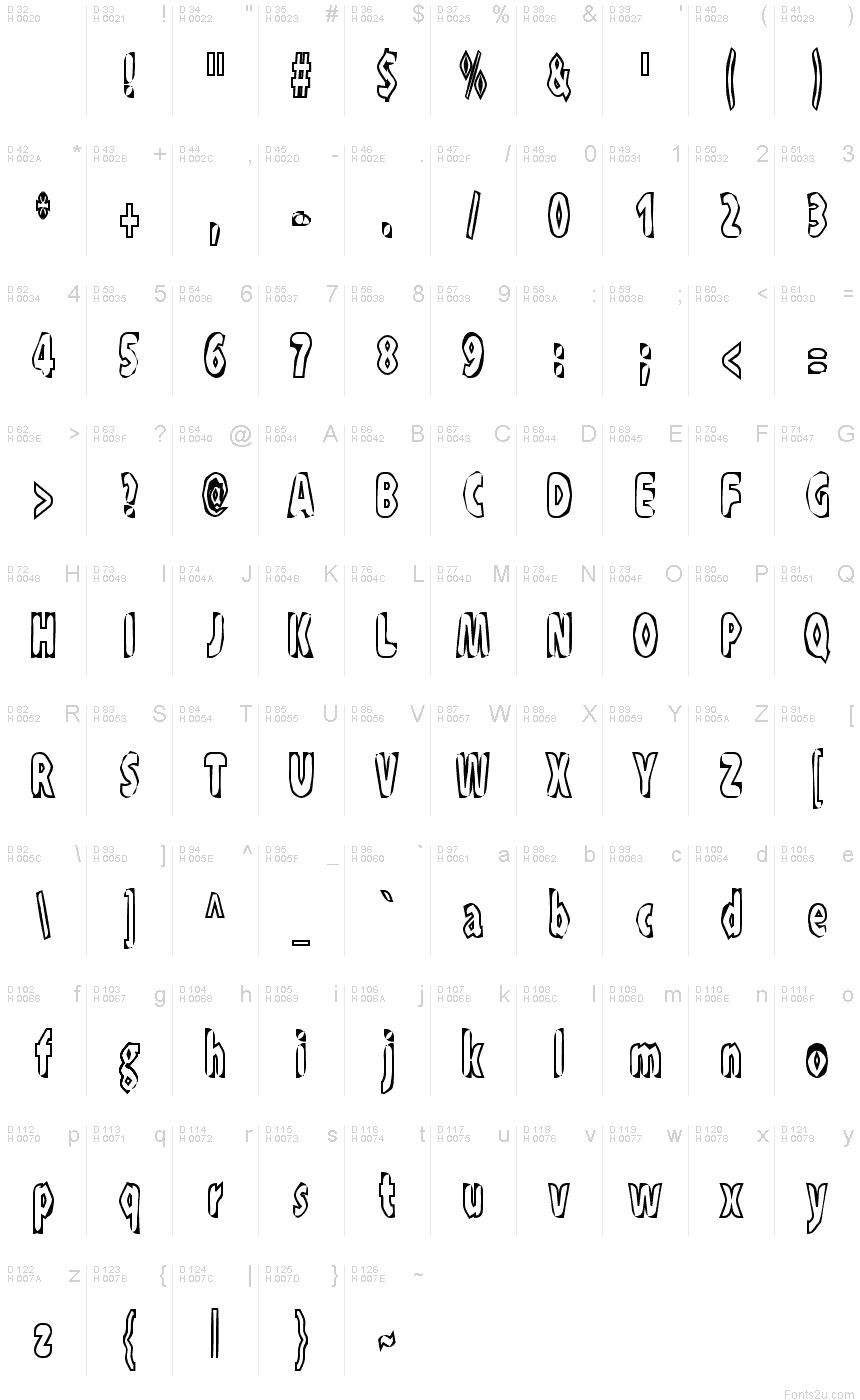
XRaytid od OMEGA Font Labs je bezplatný, deformovaný obrysový font s drsnou estetikou, která připomíná rentgenové snímky. Písmena kolísají mezi nabubřelými křivkami a staženými spoji, zatímco drsný dvojitý obrys dodává celému fontu elektrizující vzhled připomínající vystřihovánky, spíše než uhlazené komiksové tvary.
Hodí se na letáky, obálky fanzinů, loga kapel, titulkové karty, hororově-komediální obaly a krátké webové nadpisy, kde tato roztěkaná silueta nechá grafiku promluvit za sebe. Jako bezplatný font nejlépe vynikne v krátkých nápisech, monogramech a výrazných titulcích, protože nepravidelné obrysy a pokřivený rytmus udávají náladu dřív, než si stihnete přečíst samotné slovo.